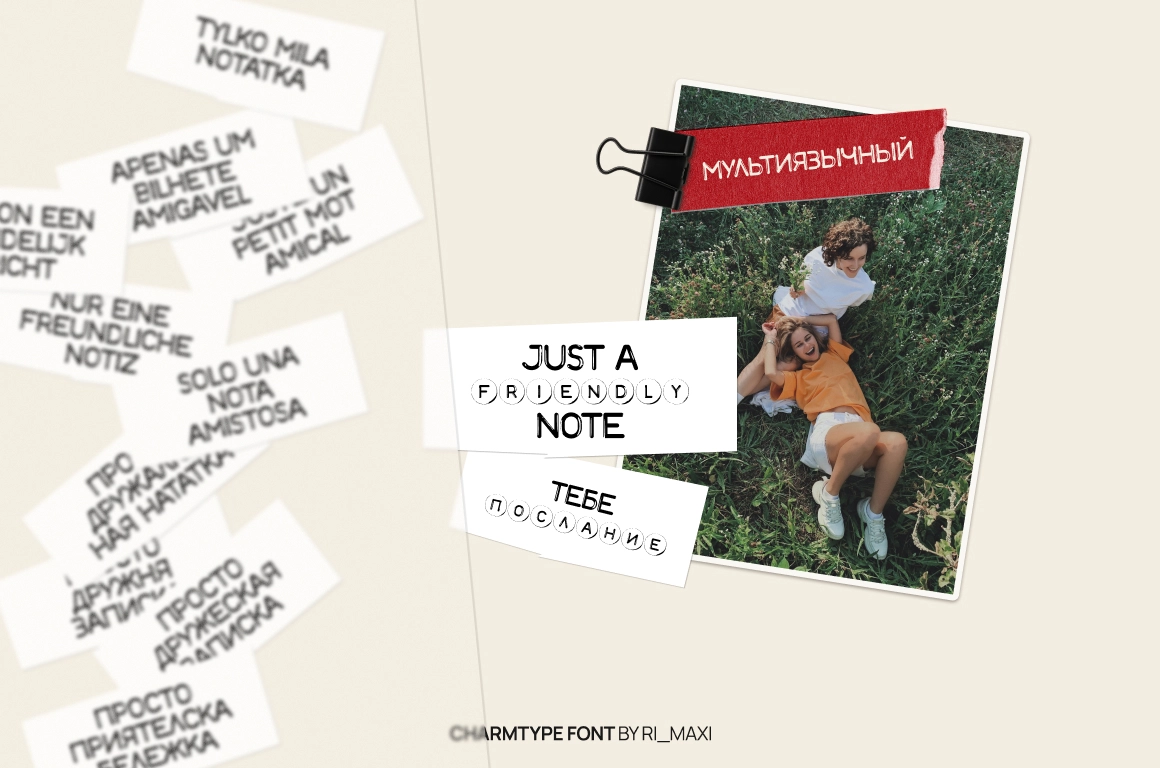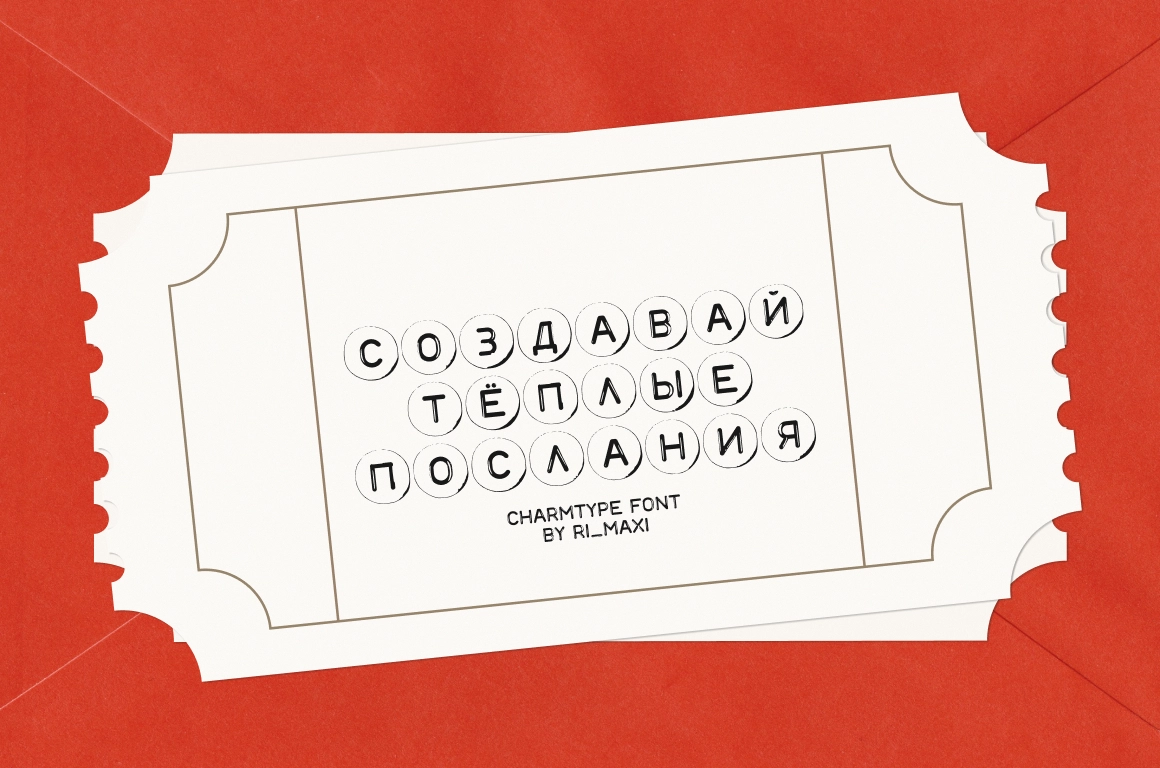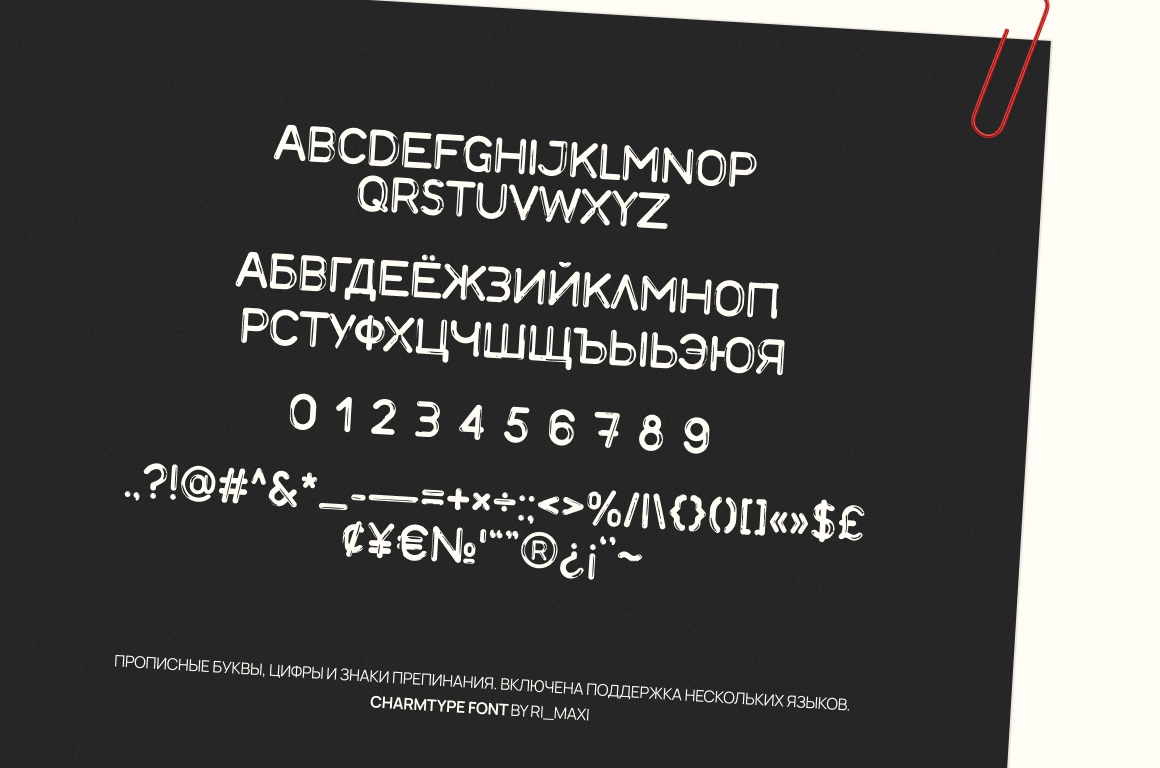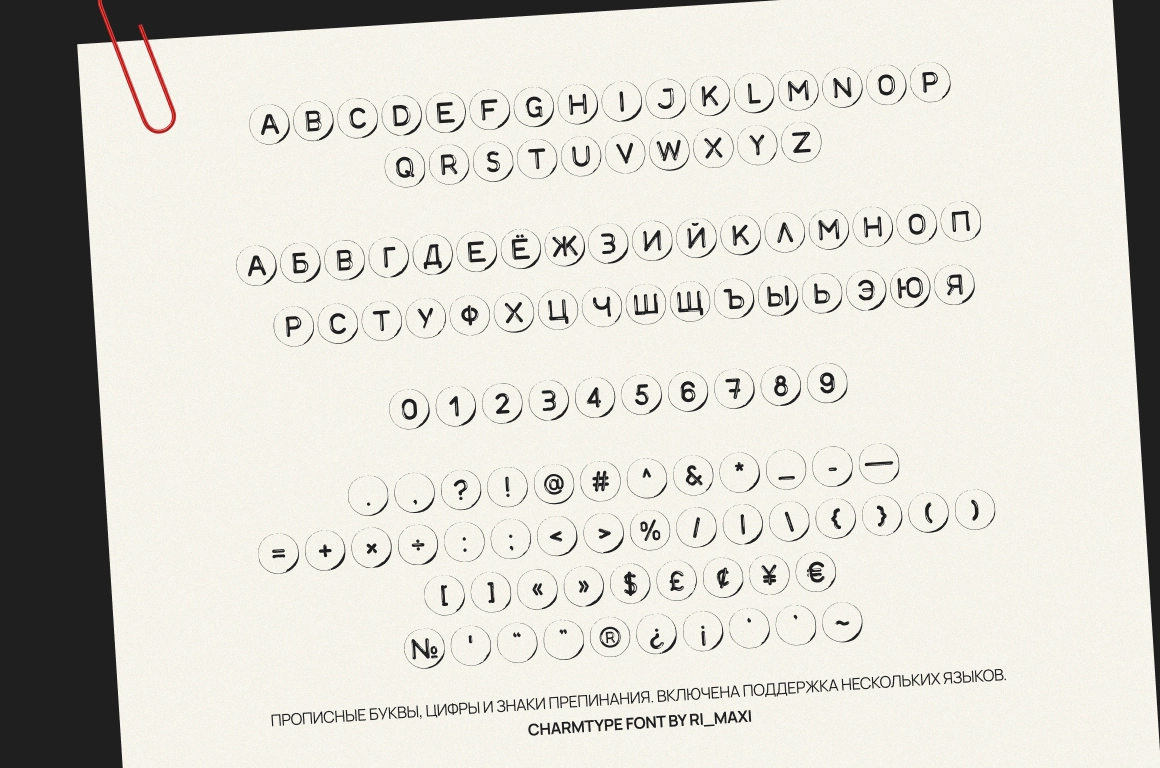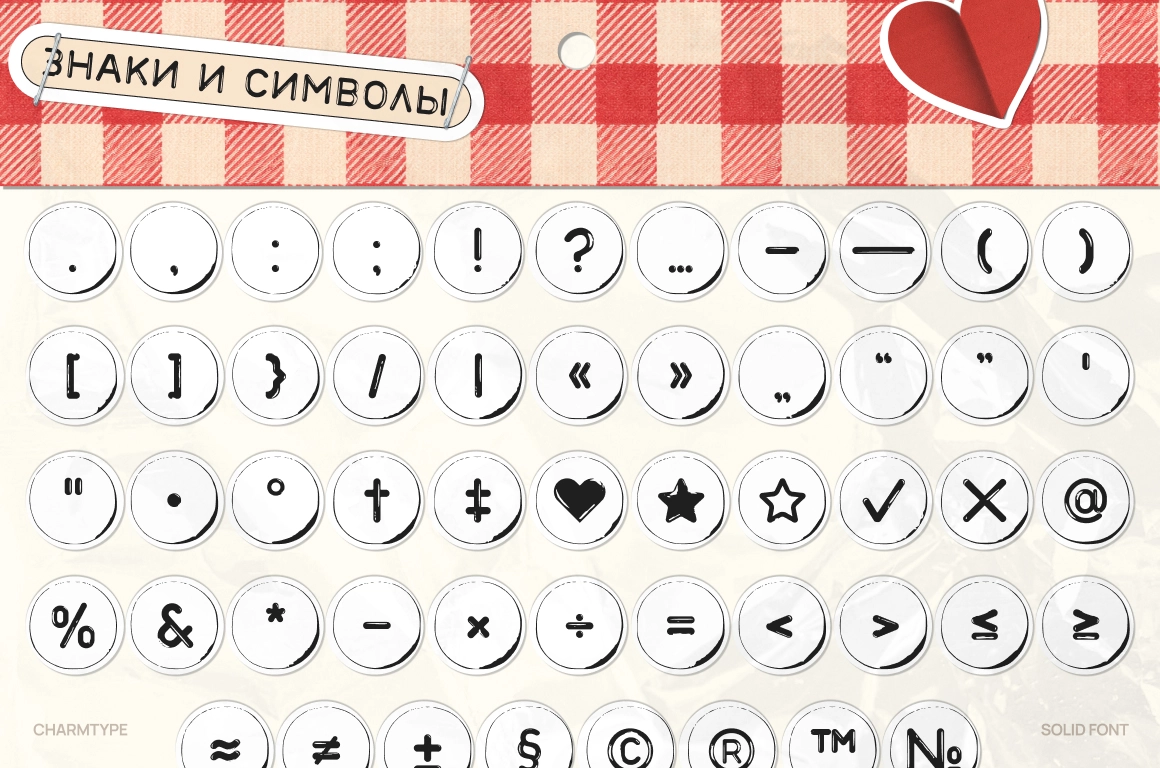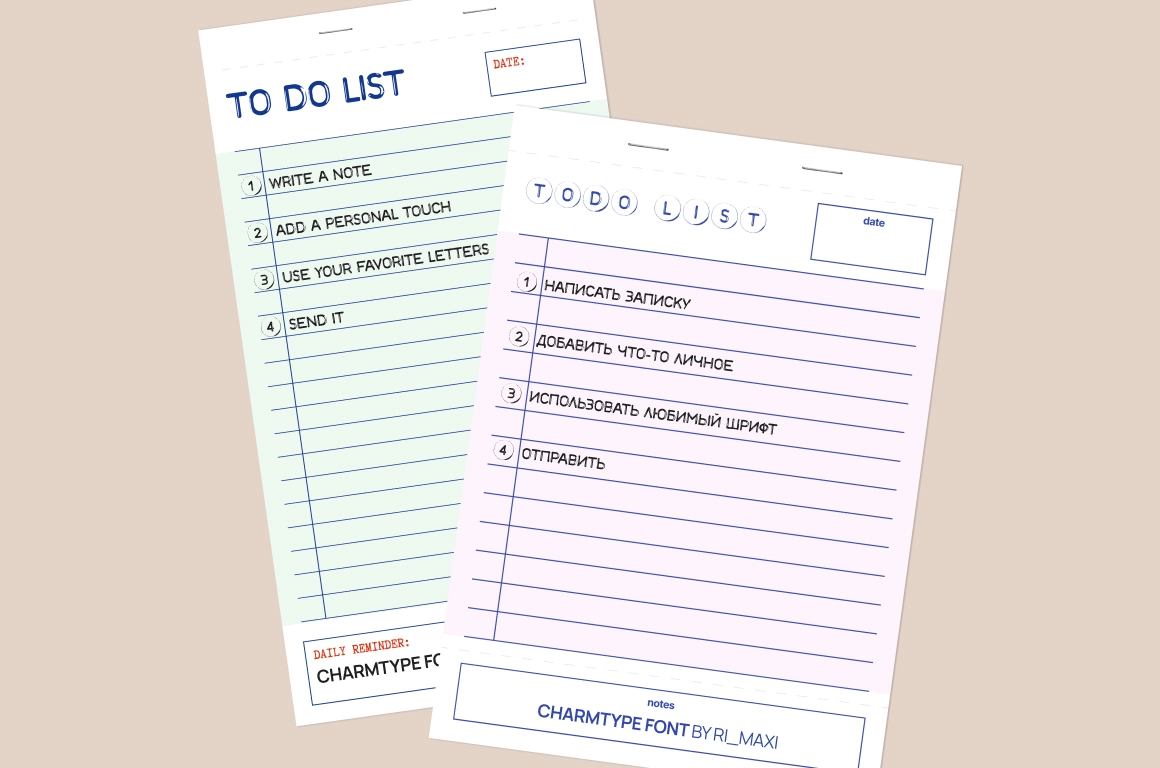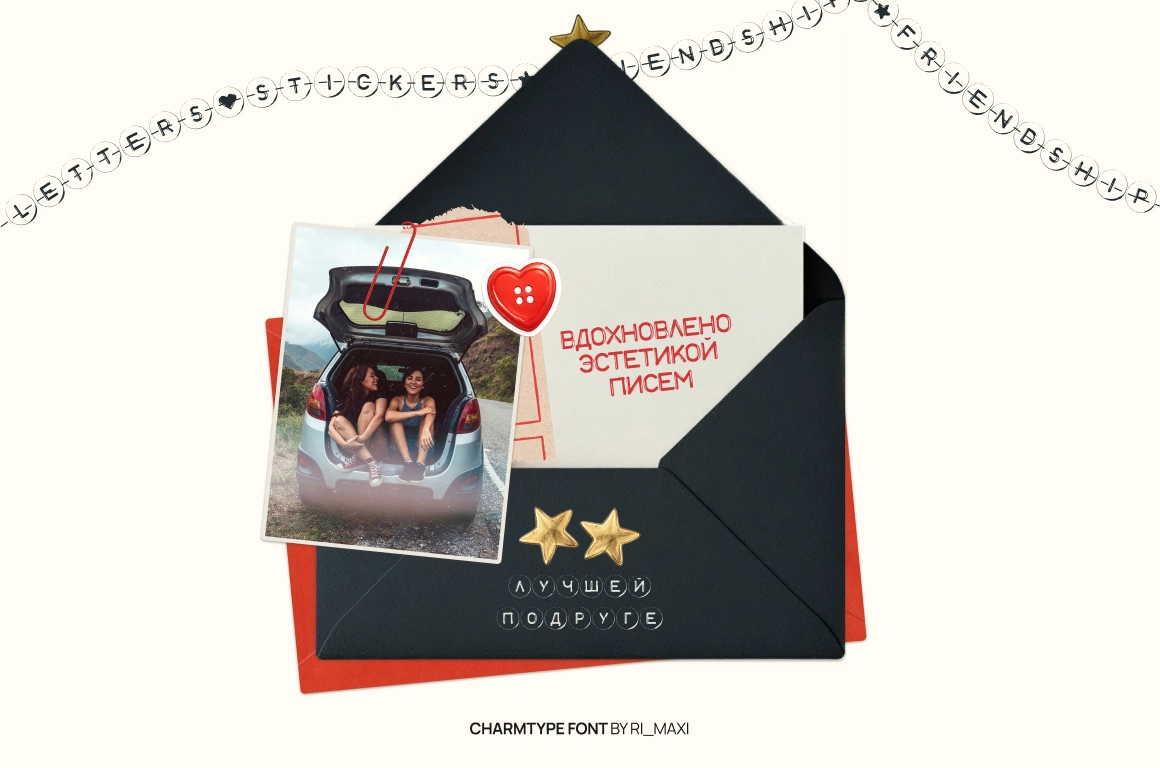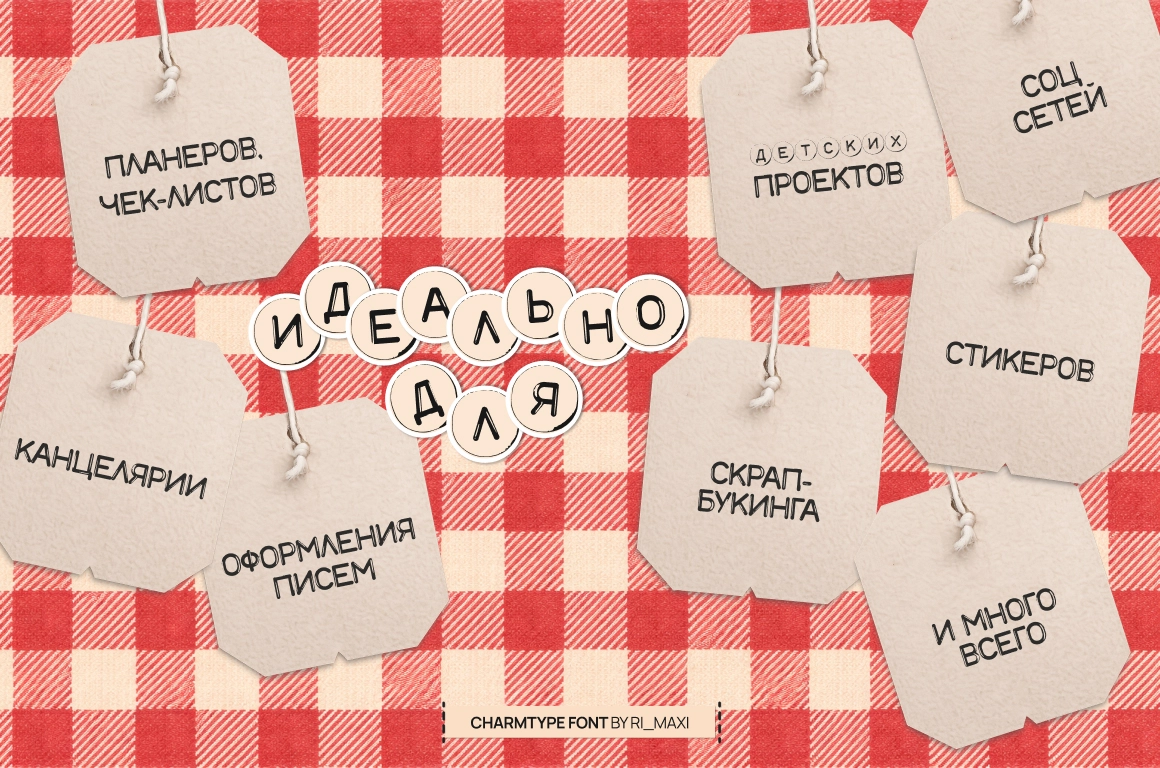
Charmtype шрифт-бусины на русском. Кириллический шрифт
Charmtype — игривый «бусинный» шрифт, вдохновлённый бумажными письмами, браслетами дружбы, стикерами и handmade‑канцелярией. Два стиля: буквы в контуре «бусины» и простые буквы без фона. Подходит для планеров, стикеров, соцсетей и DIY. Есть цифры, знаки? символы. Поддерживает кириллицу.